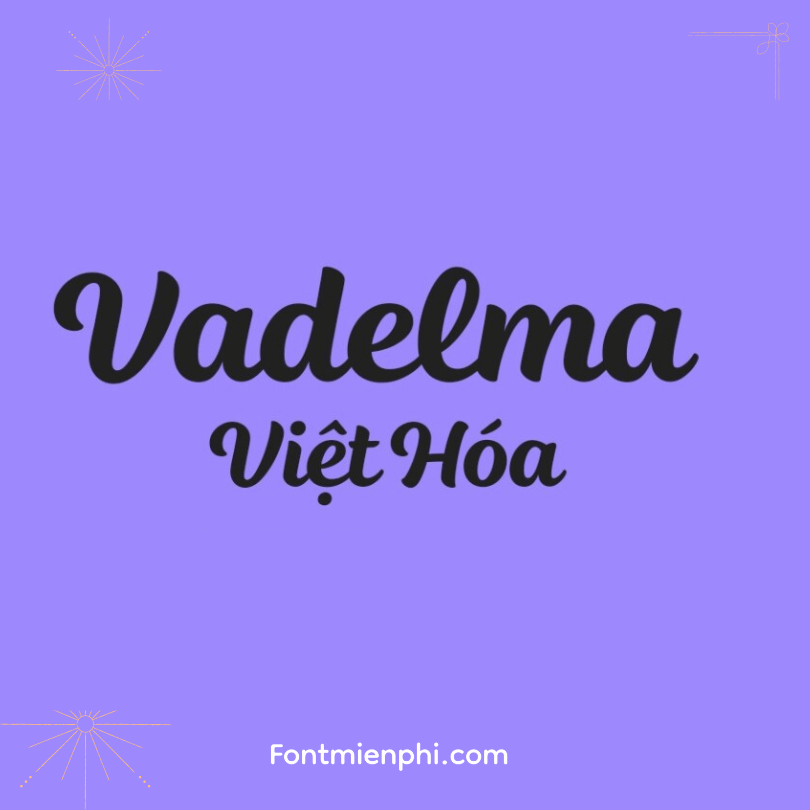
Font Việt Hoá Vadelma
Font Việt Hoá Vadelma – Phong Cách Bắc Âu Tinh Tế
Font Vadelma được Việt hóa mang phong cách thiết kế Bắc Âu hiện đại, với nét chữ thanh lịch, phù hợp cho thiết kế logo, poster, typography nghệ thuật. Font hỗ trợ đầy đủ dấu tiếng Việt, đa dạng kiểu chữ (regular, bold, italic) giúp sáng tạo không giới hạn.